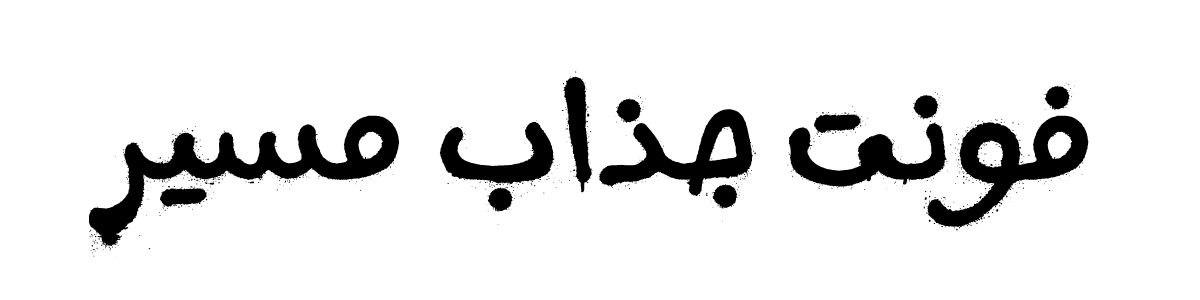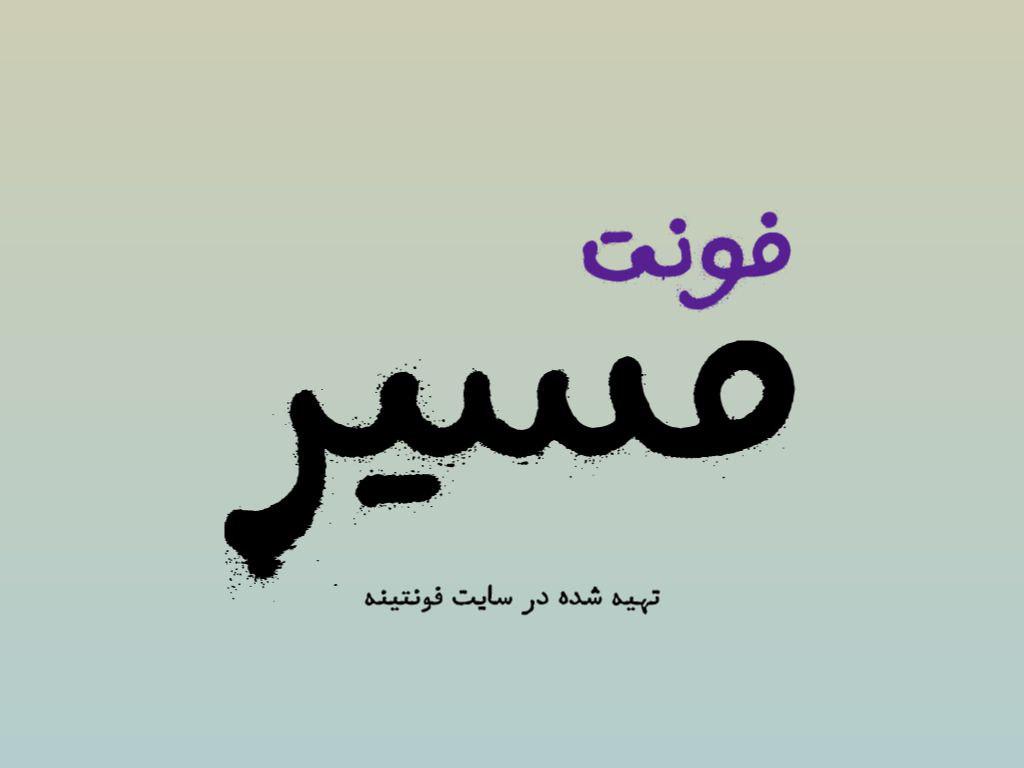
دانلود فونت مسیر
دانلود فونت مسیر در خدمت شما بزرگورارن هستیم با ارائه فونت زیبا و فارسی مسیر این فونت برای طراحی های لوگو و بنر و…. مورد استفاده قرار میگیرد.
ویژگی های فونت :
• مدرن و کاربردی
• زیبا و خاص
• مناسب طراحی لوگو و بنر
تصاویری زیبا از طراحی های خاص با فونت مسیر که برای نمایش و نمونه پیش فرضی از نمایش این فونت کاربردی طراحی شده است
فونت جذاب مسیر